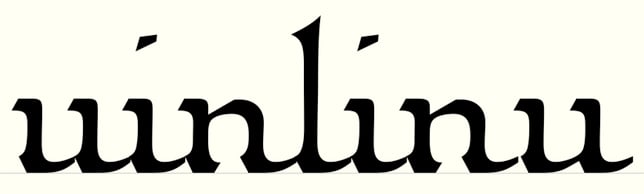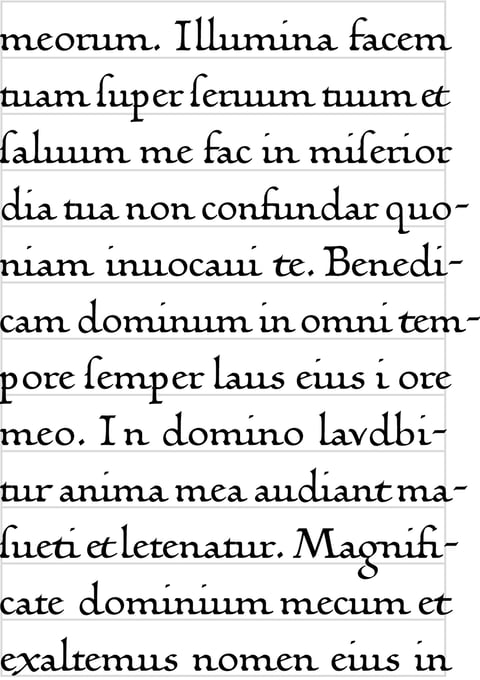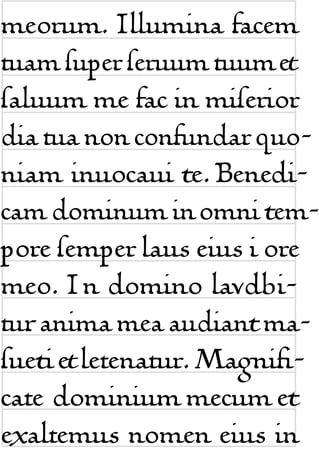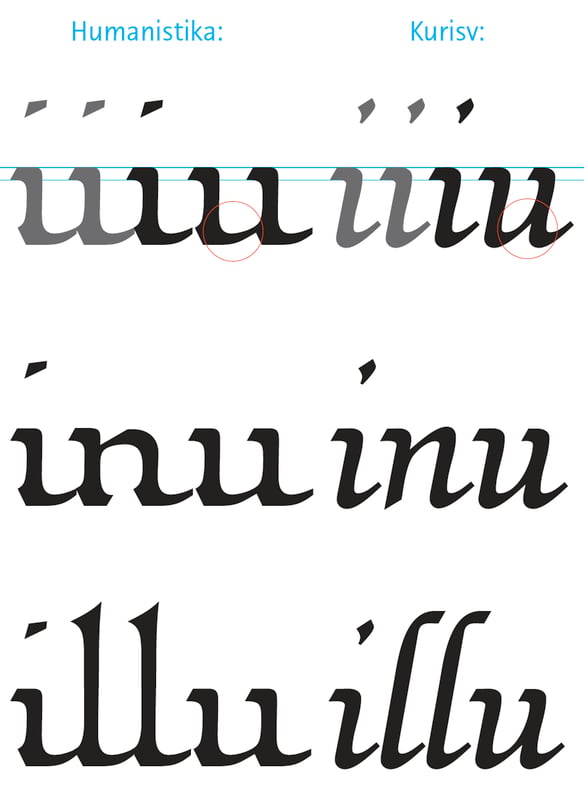
Linotype Humanistika
Eine geschriebene humanistische Minuskel vom Ende des 15. Jahrhunderts war der Ausgangspunkt für die Humanistika. Solche Handschriften dienten auch als Vorlage für die ersten gegossenen Antiqua-Druckschriften wie zum Beispiel die von Nikolaus Jenson (1470). Der kräftige Duktus mit stark ornamentalem Charakter bildet ausgeprägte Zeilen, die durch große Ober- und Unterlängen aufgelockert sind. Das DFR(Deutsche Fraktur)-Layout der Humanistika enthält das lange »s« und alle Ligaturen (Buchstabenverbindungen), wie sie vom Fraktursatz bekannt sind, sowie ein alternatives t und r. 1997 belegte die Humanistika den 2. Platz beim Internationalen Schriftwettbewerb der Linotype Library in der Kategorie Text. Adrian Frutiger als Vorsitzender der Jury hatte sie »herausgezogen« und mit höchstem Lob versehen.